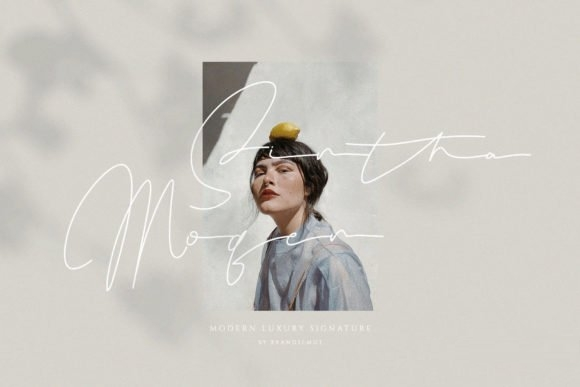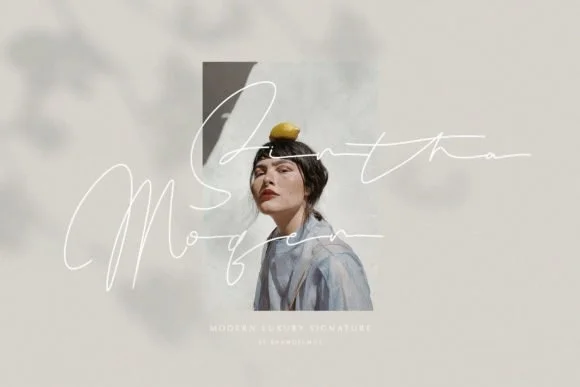
Название: Sintha Moqen Font (2021)
Sintha Moqen - это модный шрифт с тонким начертанием.
Он имеет стильный, элегантный и современный вид, который можно использовать для логотипов, брендинга, приглашений, канцелярских принадлежностей, свадебных дизайнов, постов в социальных сетях и многого другого!
Название: Sintha Moqen Font (2021)
Sintha Moqen - это модный шрифт с тонким начертанием.
Он имеет стильный, элегантный и современный вид, который можно использовать для логотипов, брендинга, приглашений, канцелярских принадлежностей, свадебных дизайнов, постов в социальных сетях и многого другого!